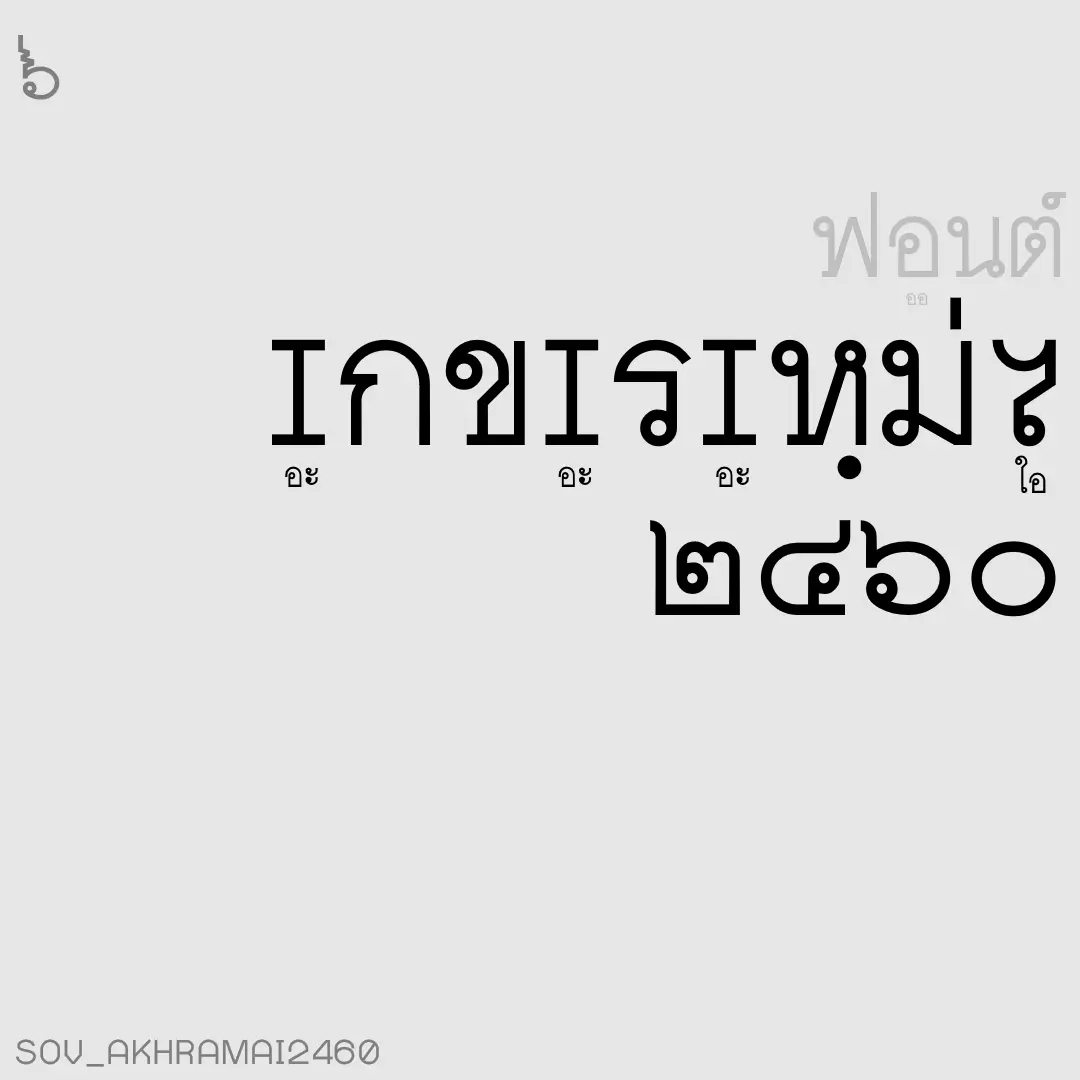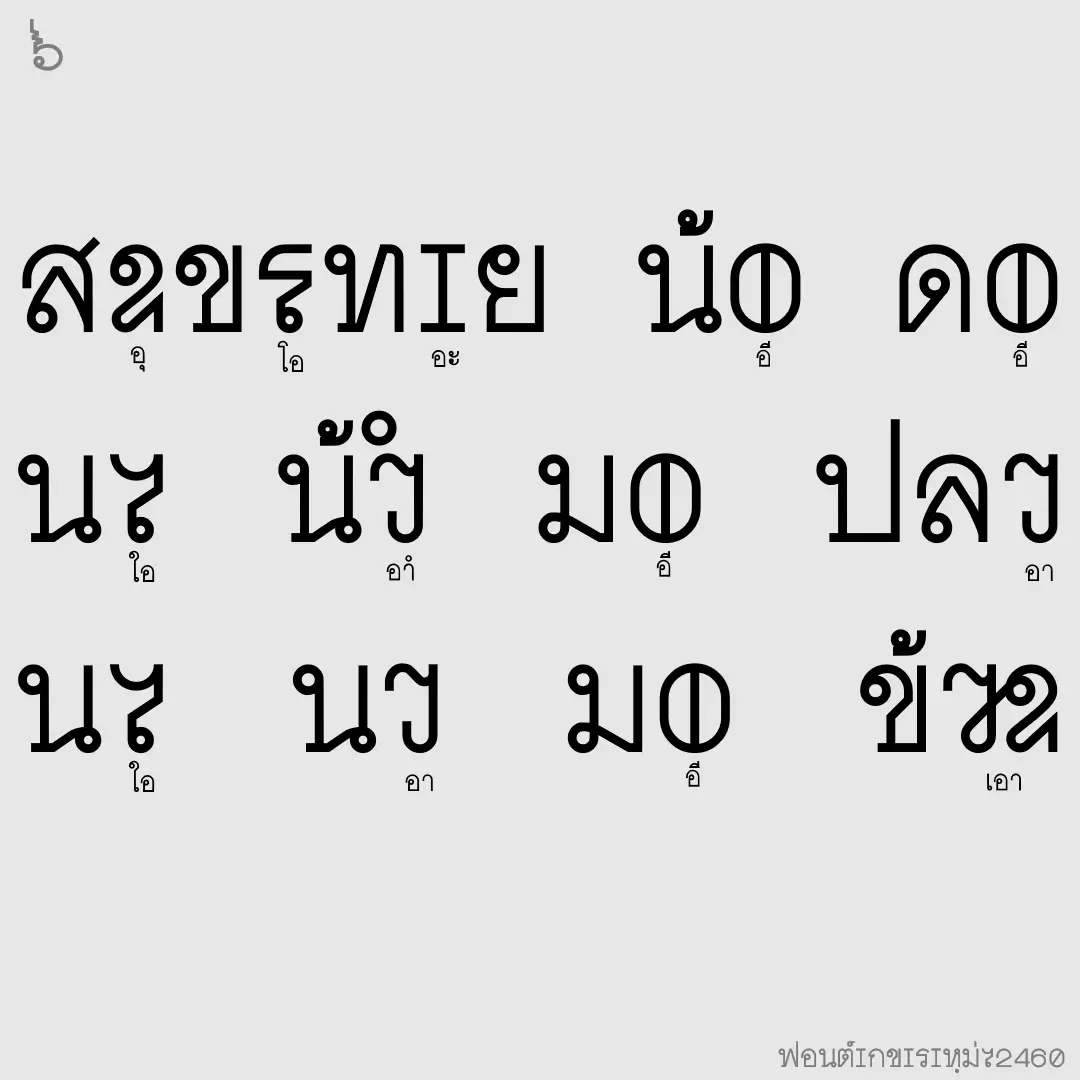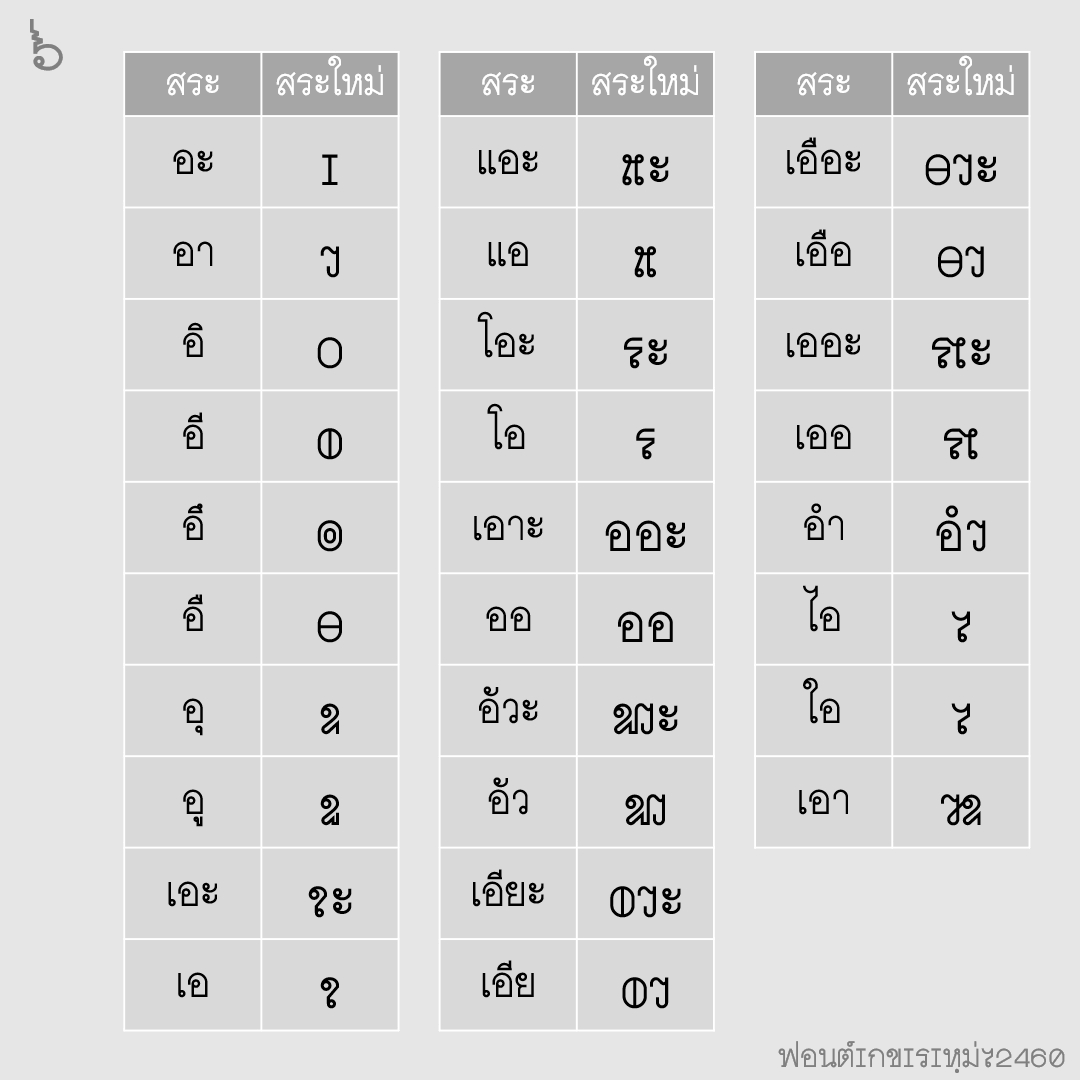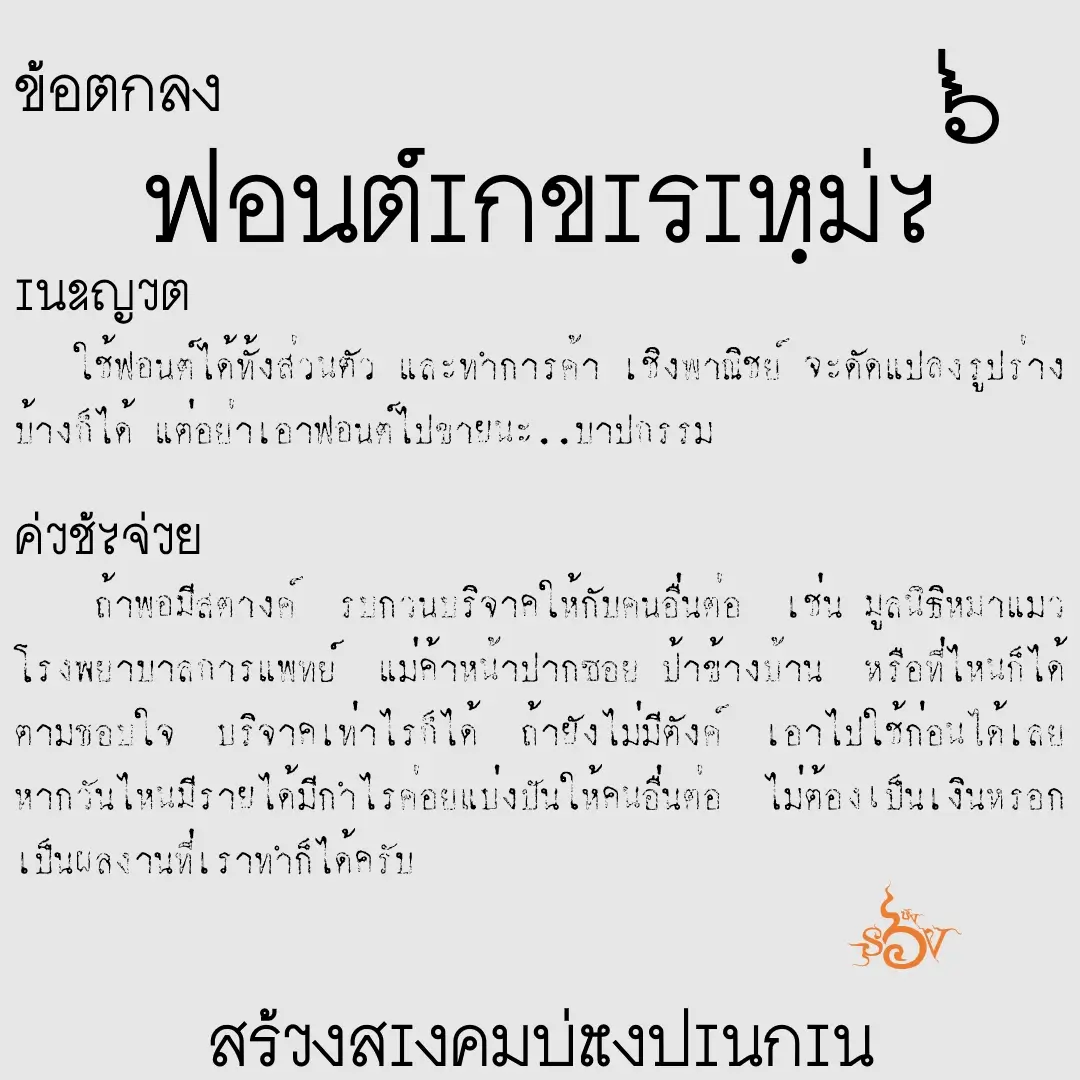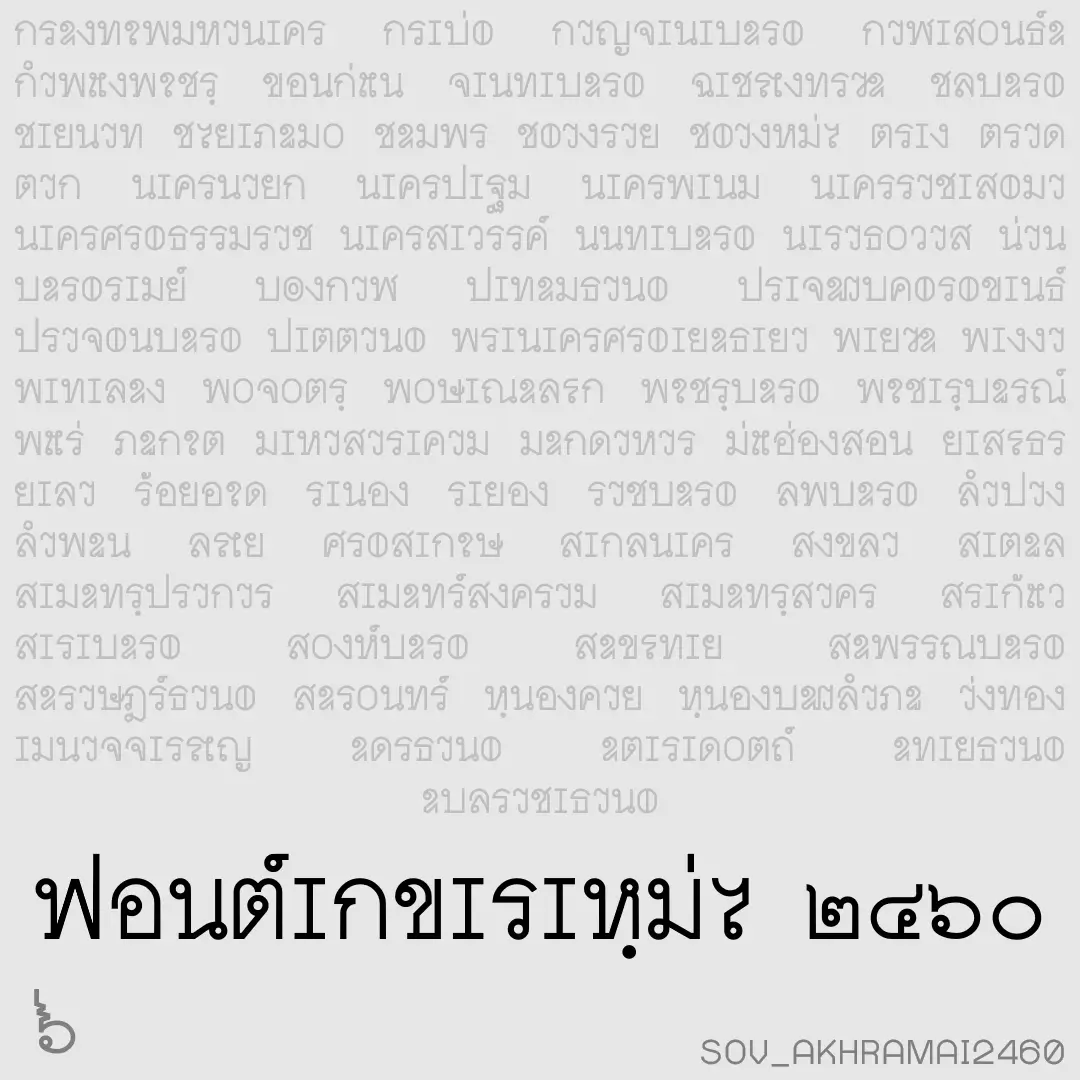
ฟอนต์อักขระใหม่๒๔๖๐ – ทดลองสร้างฟอนต์ ตามอักขรวิธีใหม่ ที่ ร.๖ ได้ประทานพระบรมราชาธิบายต่อสมัคยาจารยสมาคม ในปี พ.ศ. ๒๔๖๐
หมายเหตุ : ยังไม่คล่องใช้ฟอนต์ปรกติ คล่องแล้วหรือต้องการลบอักษรตัวเล็กๆ ใช้ฟอนต์หนา (bold)
เบื้องหลังการออกแบบ : อักขระใหม่๒๔๖๐ (SOV_AkhraMai2460)
อักขระใหม่๒๔๖๐ (SOV_AkhraMai2460)